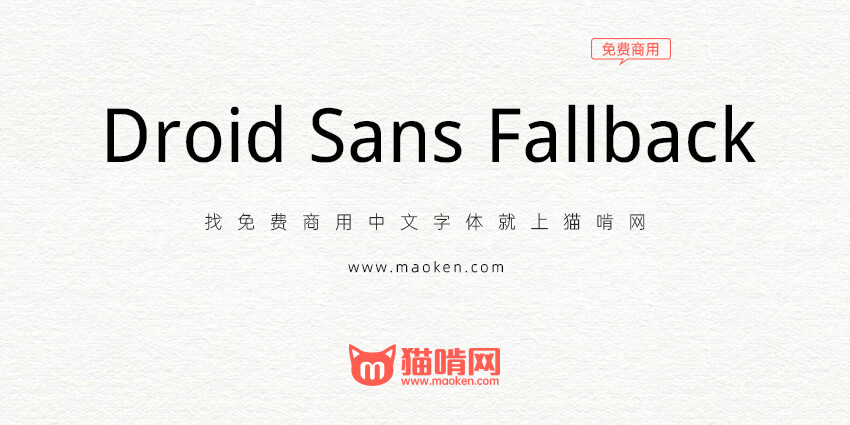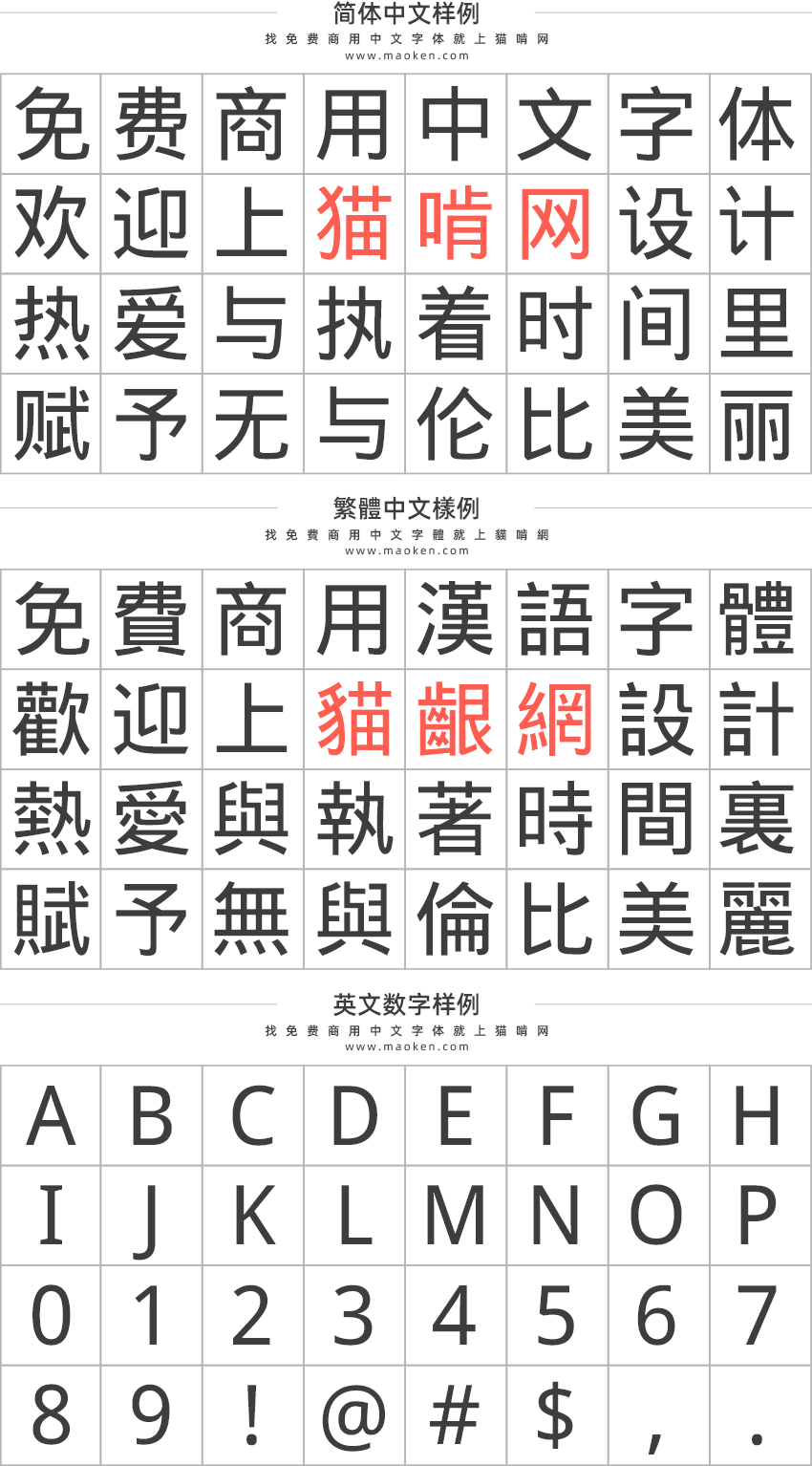
Droid Sans Fallback:第一代安卓系统默认开源字体
字体作者:Google (美国) 字体字重:1个
Droid Sans Fallback是当年Google为推出Android设备时,委托台湾华康科技(威锋数位)与字型厂商Ascender Corporation为东亚各国字符设计的一款字体,承袭了DFHeiW5-A的设计风格 。 根据 Ascender字体公司的介绍,取名Fallback是因为Droid Sans Fallback是一款作为 Droid Sans的字集补充而产生的字体,当系统在Droid Sans找不到需要的字符时会fallback到Droid Sans Fallback上。
我想到是这样的,DroidSansFallback什么时候制作GB18030-2022 L2字符集中的扩展汉字
• 这个2.60c是网友制作的~
建议删掉文泉驿那段 文泉驿补的字风格跟原版差异大,Droid Sans Fallback full 最后一个版本收录的汉字比文泉驿字数多 已经覆盖gb18030了 文泉驿微米黑已经没有价值了
字體介紹不準確修改一下
二○○四年與字型廠商Ascender Corporation共同開發Google之Android手機系統中的中、韓文。
——摘自華康官網———–
Ascender現在已經成為蒙納的子公司
修改一下 這是共同開發的並非華康一個公司完成的
沒想到遊戲公司SNK在其推出的最新一款刀劍挌鬥遊戲「侍魂-曉」放著思源黑不用卻使用「Droid Sans Fallback」作為遊戲中文字幕